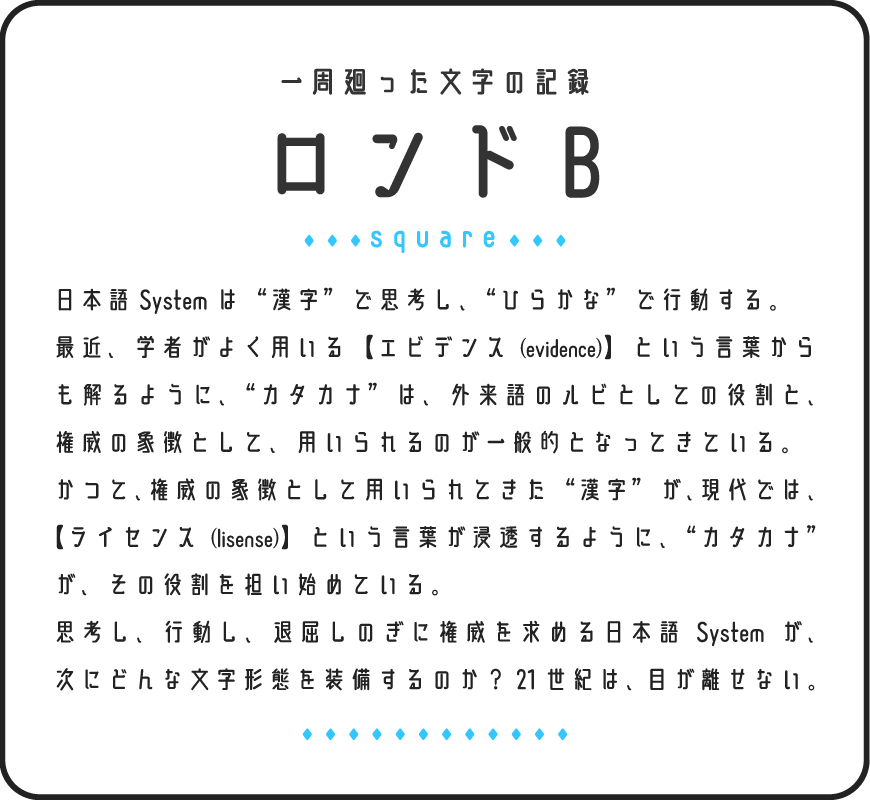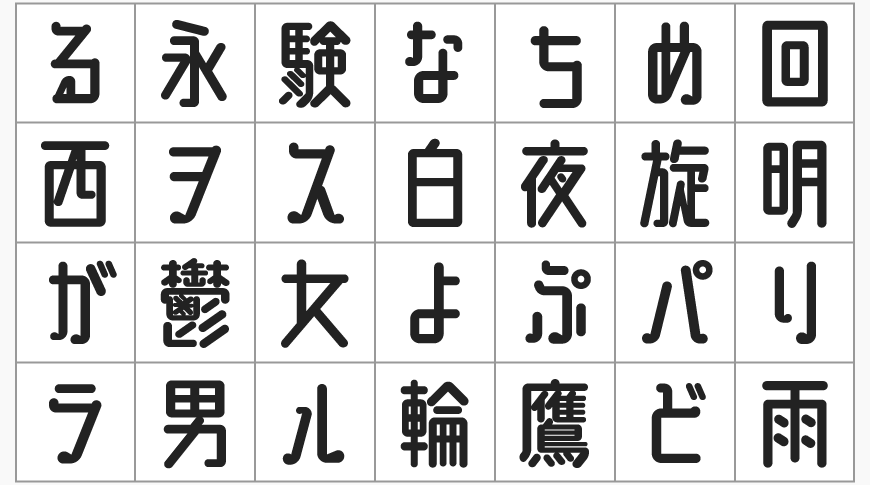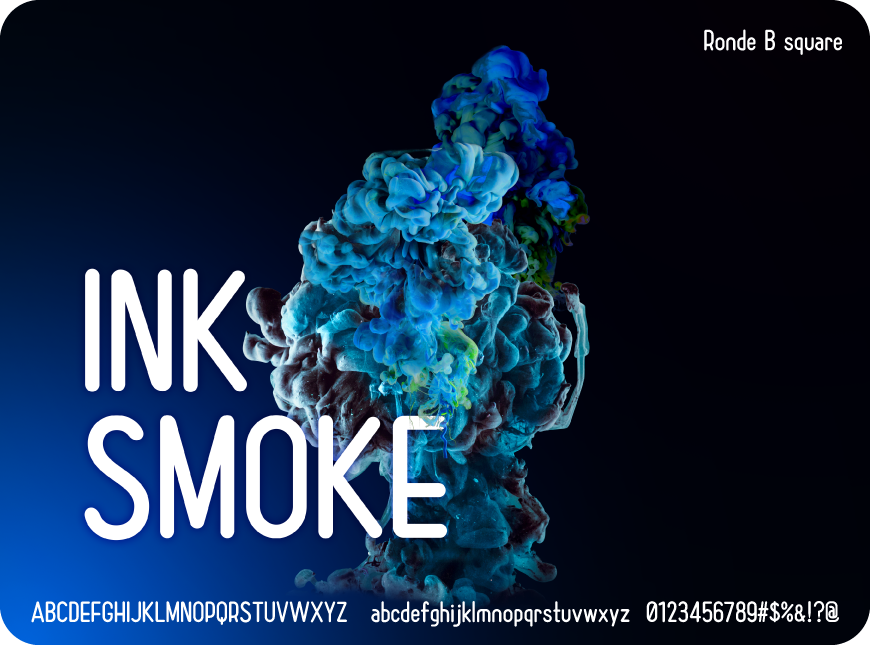
「廻想体B」是基于「廻想体」改造开发的一套字体,他与「廻想体」不同之处是这一款字体是圆滑型字体,文字给人一种秀丽纵长的印象。制作这套字体主要是因为作者在街上、WEB、报纸等地方,看到自己开发的「廻想体」被使用的时候感觉到“啊,其实是希望这套字体是圆的吧!”。
字体特色
虽然是日本字体,但是当中收录了约3700字汉字。JIS第1水准(2965字),JIS第2水准(486字) ,其它(16字)。我们平常使用可能会缺不少简体字符,毕竟日本的汉字使用跟中国的汉字还是有点不同的 ,但在可免费商用的字体极度缺乏的时代,使用这些日本字体还是不错解决方案。